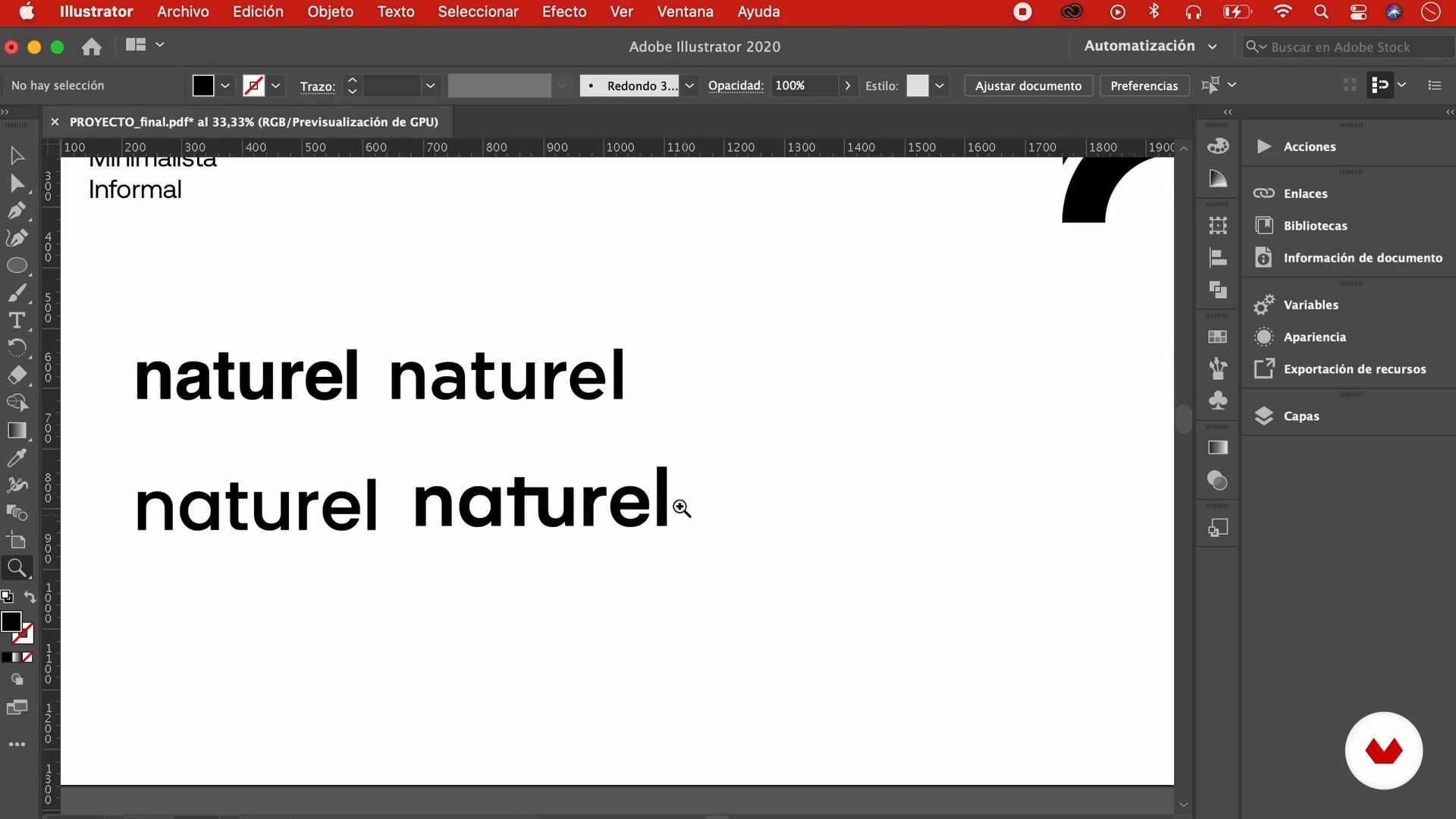
Design de identidade visual com traços grossos
Tipografia
Sobre a videoaula: Tipografia
“A tipografia é um elemento muito importante para qualquer logotipo e design gráfico. Para ajudá-lo a escolher o tipo de letra para o seu logotipo, explicarei como se distinguem os diferentes tipos de impressão e darei algumas dicas para escolher um.”
Nesta videoaula, Berch Kotogian aborda o tópico: Tipografia,que faz parte do curso online da Domestika: Design de identidade visual com traços grossos. Aprenda a criar logotipos de forma simples e criativa a partir da síntese de ideias e de traços grossos.
“Tipografia Nesta unidade eu vou te ensinar como escolher a tipografia e definir a cor. Além disso, colocarei o logotipo no contexto e mostrarei como faço a apresentação final. Nesta aula vou mostrar qual a fonte ideal para o logotipo e como aplicá-lo. Classificação Em qualquer projeto de design que você esteja fazendo, É importante conhecer e ser capaz de classificar as diferentes famílias tipográficas. O tipo de letra de uma marca deve ser selecionado com cuidado pois dependendo da seleção estaremos passando uma mensagem bem diferente. Podemos classificá-los como Serif. Esses tipos de letr...”